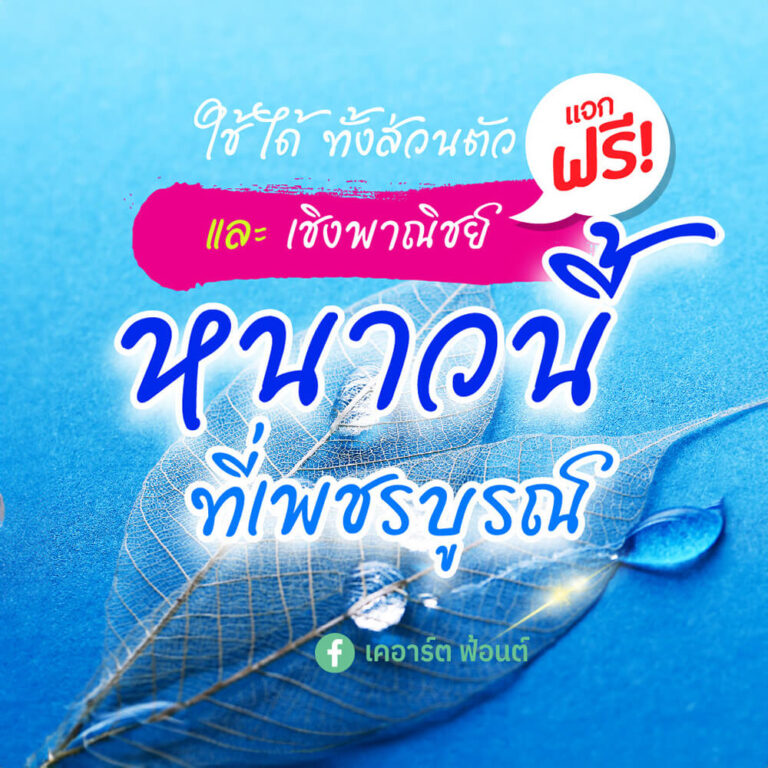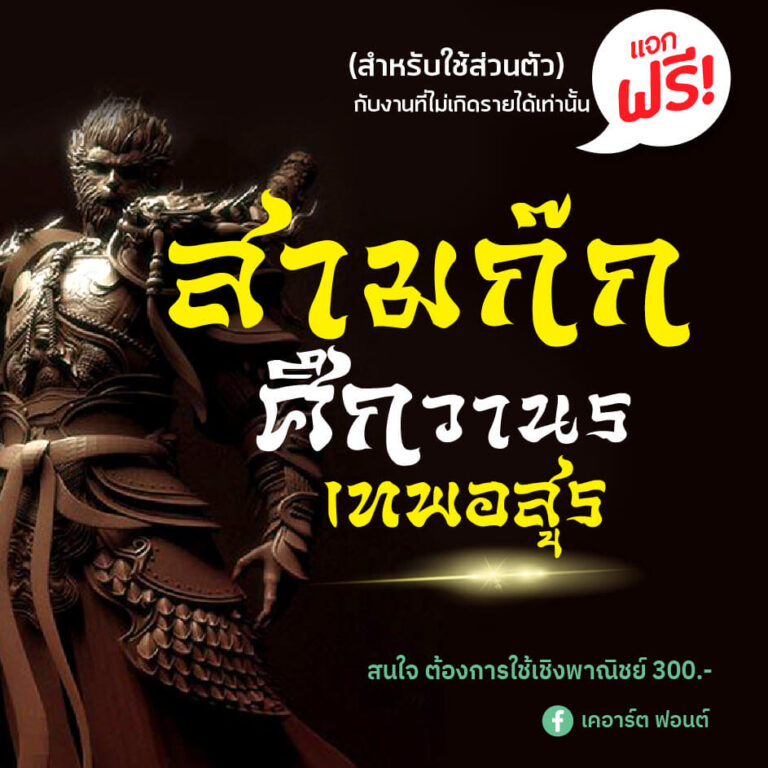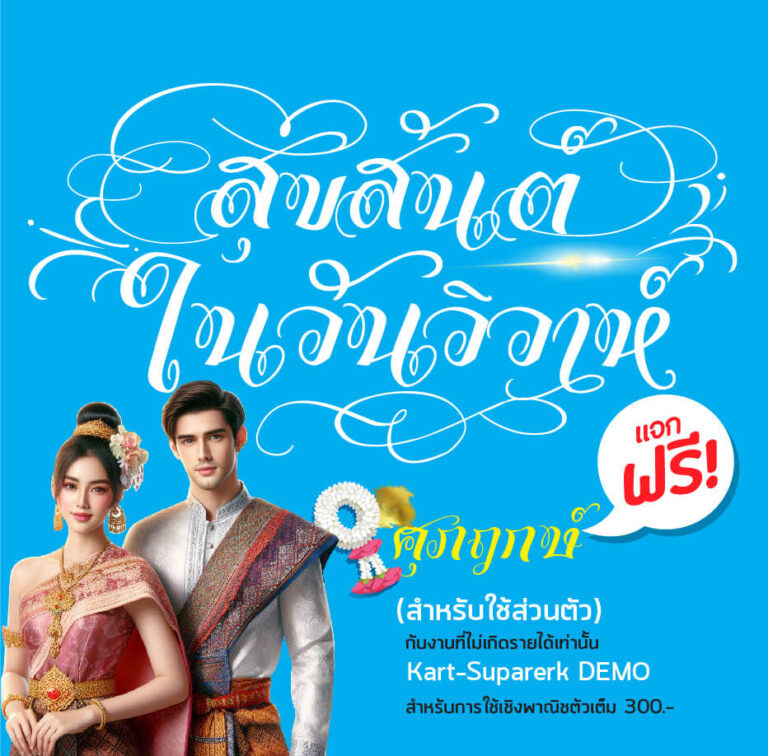
เคอาร์ต ลายมือปกเพลง (Kart-Thai raimue2)
เคอาร์ต ลายมือปกเพลง (Kart-Thai raimue2) เป็นฟอนต์ที่เขียนขึ้นอยากให้ดูเป็นหางตวัดมากขึ้นจากผลงานเดิม (เคอาร์ต ลายมือหวัด)เน้นกลุ่มตัดต่อวีดีโอ งานภาพถ่ายต่างๆ ไม่ค่อยเหมาะกับอักษรที่เขียนเป็นข้อความยาวๆ
เคอาร์ตสถาปัตย์ (Kart-Satapat) เป็นฟอนต์ที่เขียนขึ้นจากแรงบันดาลใจลายมือ อาจารย์ปัญญา เพ็ชรชู ศิลปินสาขาจิตรกรรม ของโรงเรียนเพาะช่างชอบและจำติดตาเลย คิดว่าทำได้หลายประโยชน์เลยทำมาเป็นฟอนต์ครับ
เคอาร์ต ลายมือหวัด (Kart-Thai raimue) เป็นฟอนต์ที่เขียนขึ้นจากความชอบลายมือ ตั้งใจเขียนมานาน ปรับแก้เพราะการเป็นฟอนต์ที่ต้องหลบหางเป็นอะไรที่ยาก
เคอาร์ต อันยอง (Kart-Anyong) เป็นฟอนต์ที่เขียนขึ้นจากปากากพู่กันในอารมณ์เกาหลี แอบติดเซบ้างให้ดูสนุกฝากติดตามผลงานด้วยครับ
เคอาร์ต เหนือดวง (Kart-Nuea Duang) เป็นฟอนต์ที่เขียนขึ้นจากลูกเพจอยากให้เขียนฟอนต์ในอารมณ์ใบงาน พิธีพุทธาภิเษก พระเกจิต่างๆ เน้นอักษรที่มีอารมณ์ปลุกเสก เน้นใช้กับข้อความไม่ยาวมาก เลยบรรจุลายกนกลงในฟอนต์เพื่อให้ง่ายกับการใช้ครับ สามารถดีดฟอนต์ในอักษรให้เป็นลายกนกได้เลยครับ ฝากติดตามผลงานด้วยครับ
เคอาร์ต โขนไทย (Kart-Thai-Khon) เป็นฟอนต์ที่เขียนขึ้นจากอารมณ์โขนไทย จังหวะจะดูย่อขาไปด้านหน้า วางเท้าแบบผู้แสดงโขน สามารถใช้กับข้อความอักษรยาวมากได้ ในส่วนภาษาอังกฤษก็ออกแบบมาเพื่อใช้กับโลโก้ร้านอาหารไทย กิจการไทยเป็นหลัก เน้นใช้กับข้อความไม่ยาวมาก
เคอาร์ต ชวาลศิลป์ (Kart-CHAWANSILP) เป็นฟอนต์ที่เขียนเพราะคิดถึงอาจารย์ชวาลศิลป์ อาจารย์ผู้มีแต่ให้สำหรับวงการป้ายที่ผมอยู่ขอบคุณในความน่ารักและไมตรีจิตส่งผ่านในทุกความรู้ให้กับคนวงการป้ายมาตลอดครับ รำลึกถึงเสมอ ครูของวงการป้าย ชวาลศิลป์ศรีราชา จากใจศิษย์คนหนึ่ง
เคอาร์ต วิษณุ (Kart-Vishnu)เป็นฟอนต์ที่เขียนขึ้นเพราะไอ้เราก็เด็กช่างด้วยมั้ง อารมณ์แรกที่อยากได้คือสไตล์ไทยๆ แนวเด็กช่าง อารมณ์ร็อกหน่อยแต่ต้องคุมแนวไทยให้ดูดุๆ หน่อย เลยได้ผลงานชิ้นนี้มาครับ หวังว่าสายสกรีนเสื้อคงชอบครับ
เคอาร์ต โบราณนิยม (Kart-Boran Niyom)เป็นฟอนต์ที่เขียนขึ้นเพราะชอบแนวอักษรสมัยก่อน อย่างคำว่า โกปี๊ จิ๊กโก๋ โอยั๊วะ นั่งมองแล้ว ไม้ตรีในอักษรป้ายสมัยเก่ามันมีความขลังดี เลยมาเขียนต่อยอดให้มันลงตัว
ฟอนต์งานแต่งมีหางฟอนต์อารมณ์ อ.จินดา เนื่องจำนงค์เจ้าของเพจ “อักษรตัวเขียน” ที่ผมก็เป็น FC ท่าน จนพัฒนาเป็น ศุภฤกษ์ ในปัจจุบันครับ แนวคิดในการออกแบบคือผมไม่สามารถสร้างหางประกอบได้เหมือนท่านเลยเอาหางที่พอคิดได้บรรจุลงในฟอนต์ซะเลยครับ
แรกเริ่มเดิมที ชอบชื่อหนังโปสเตอร์เรื่อง “ธี่หยด” เลยอยากทำแนวๆ พุทธคุณของขลัง ออกแบบไว้สำหรับใช้ในงานป้าย งานศาสนา หรือใช้ในโอกาสต่างๆ แจกฟรี! สำหรับใช้ส่วนตัวครับ
แรกเริ่มเดิมที กะจะเขียนฟอนต์อารมณ์ซุนหงอคง วานรเทพไร้พ่าย งานจะเป็นแนวหางสะบัดอารมณ์ไซอิ๋วแต่งชุดรบพร้อมปะทะพลิ้วไหว ออกแบบไว้สำหรับงานป้ายไวนิล รอบที่ใช้จริงตอนแรกๆ ก็เทศกาลถือศิลกินเจครับ เขียนไปเขียนมาจบที่สามก๊กเฉยเลย 555 ไม่ไปต่อละ จะไหลไปงานซีรีส์เกาหลีละ
เคอาร์ต รามเกียรติ์ เป็นฟอนต์งานไทยที่ออกแบบให้ใช้งานป้ายได้ด้วย โดยเฉพาะงานฉลุอักษรงานไม้ CNC งานป้ายอักษร ใช้เวลาเขียนนานพอสมควร เป็นงานยากสำหรับงานหลบหางอักษร เขียนแก้มานับไม่ถ้วน
ฟอนต์จีนแนวอาหารงานไวนิลร้านป้าย แรกเริ่มเดิมทีเขียนไว้ใช้เองกับแจกเพื่อนๆ ร้านป้าย คือเขียนโดยอิงไว้ใช้กับป้ายจำพวกอาหารเป็นหลักเลยครับ แนวคิดคือดูไม่จีนจ๋าๆ แบบปลายพู่กันงานมันจะออกแนวใช้ปากกาเมจิกเขียน ซึ่งแนนอนว่ายังไม่สมบูรณ์มือใหม่หัดทำ
นี่เป็นฟอนต์แรกที่แจกครับ แน่นอนว่ายังไม่สมบูรณ์เพราะเป็นมือใหม่หัดทำ ฟอนต์นี้ใช้เวลา 6 เดือนหลังเลิกงาน ค่อยๆ ทำ ทำบ้างหยุดบ้าง มีตกหล่นบ้างขออภัย